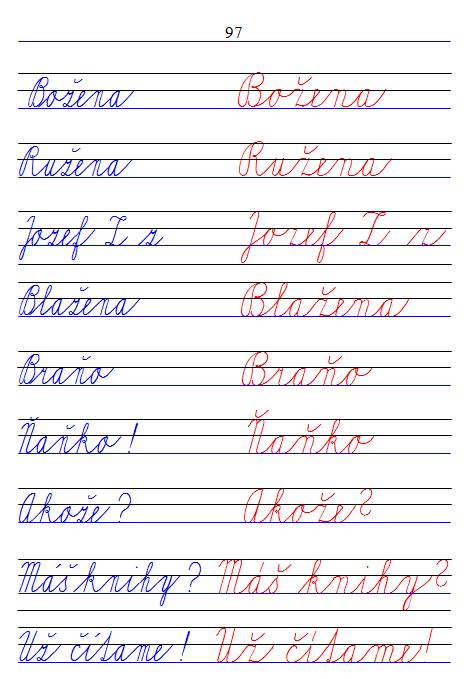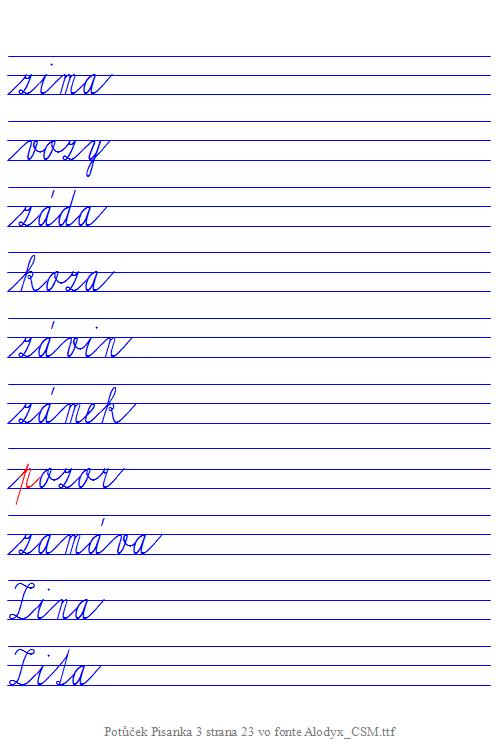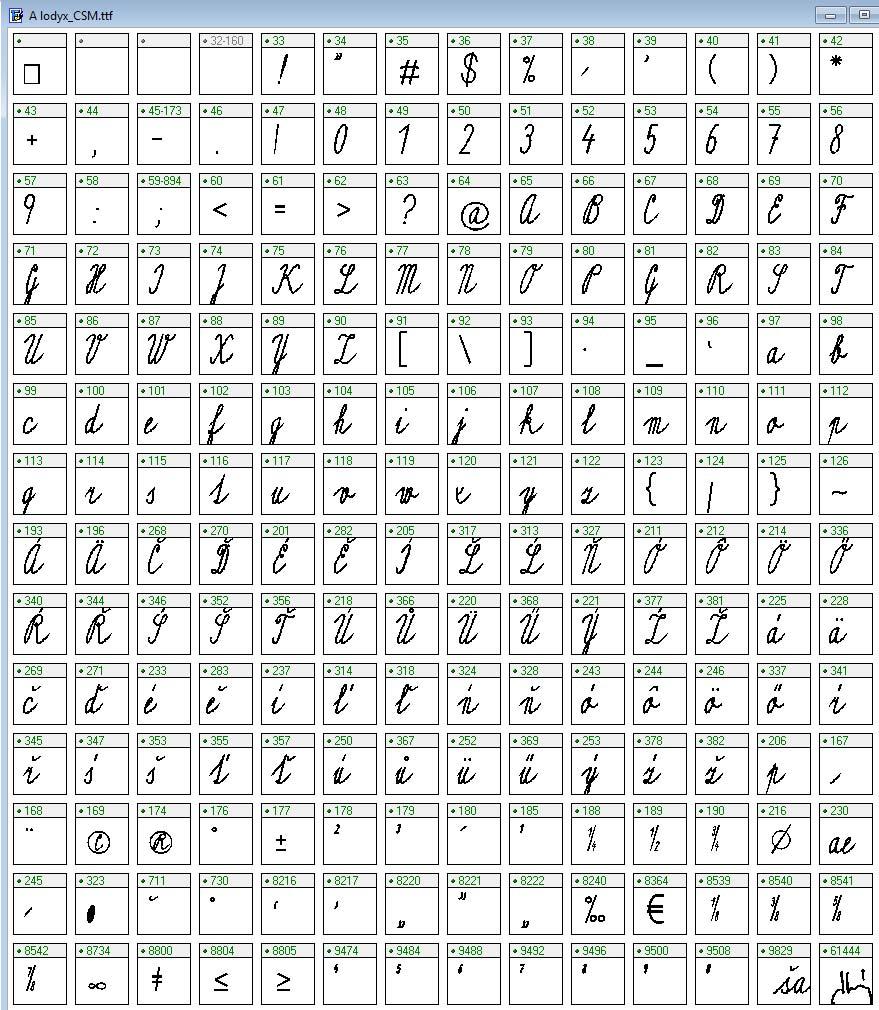
1 Font Alodyx úprava na verziu so slovenskými a maďarskými písmenami Stanislav Fila. Centrum pedagogicko-psychologického poradenstva a prevencie, Banská Bystrica. Font možno stiahnuť z lokácie: V súbore cti_me.txt je toto: Psací písmo TRUE TYPE alodyx. Zatím to nejlepší běžně dostupné ČESKÉ psací písmo. Jelikož některá psací písmena se v češtině napojují od spodu a některá ne, je zde použita klávesa ( VEDLE ENTERU! ) pro změnu tohoto napojení. Instalace pro méně znalé např: start/ovládací panely/písma/soubor/nainstalovat nové písmo lokace - vybrat Zařazeno do projektu - didaktické pomůcky. Používa teda len jednu nábehovú čiarku rovnakú pred písmenami ako aj za písmenami, ktoré to potrebujú. Túto čiarku dal autor pod klávesu. Tzv. doťahovaciu čiarku na konci písmen nepoužíva. Písanie v ňom je teda jednoduchšie ako vo fonte Abeceda.ttf. Autor fontu nie je známy. Iba krstné meno Ladislav a nickname (prezývka) šaman. Podpis a nickname má pod kódmi: Nicname: Priezvisko: Krstné meno: Pretože font neobsahuje písmená slovenskej a maďarskej abecedy, tak som ich tam doplnil. Font som nazval A lodyx_csm (české-slovenské-maďarské písmená). Vo fonty boli niektoré Postripts Name česky. Najprv som ich premenoval na anglické, kvôli prehľadnosti pri pridávaní nových znakov. Pomôcka: acute = dĺžeň ú caron = mäkčeň č ring = kolečko ů circumflex = vokáň ô dieresis = dve bodky ü hungarumlaut = dve čiarky ű slash = lomítko / tilde = vlnovka ~ 1
2 Pritom som odstránil niektoré chyby. 1. Písmeno kód 318 lcaron ľ (l s mäkčeňom) bolo tam f : Opravil som to takto: 2. Znak ś (saucute) bol namapovaný ako scircumflex ŝ (kód 349). Dal som ho pod sacute (kód 347). 3. Znak dvojbodka nebol namapovaný. Namapoval som ho pod Postscript Name colon, kód 58. 2
3 Dorobil som tieto znaky: Ä Ľ Ĺ Ó Ô Ö Ő Ŕ Ü Ű Ź 11 znakov ä ĺ ľ ô ő ŕ ü ű ź 9 znakov quoteright (Alt ) 1 znak doťahovacia čiarka na konci písmen: pod Ampersand & kód Alt znak Prerobil som české p na slovenské a pôvodné české p som dal pod kód Alt spolu 1 znak 23 znakov. Vo fonte je znak nacute teda malé n s dĺžňom, ktoré sa v českej abecede nevyskytuje. ń kód 324. Nechal som ho tam. Pridal som tam aj pomocný ladiaci znak, ktorý som dal pod Nacute Ń kód 323. Problém sklonu dĺžňov. Keď sa na pôvodný font pozrieme, resp. napíšeme v ňom nejaký text, vidíme, že smer dĺžňov je príliš doprava, teda nelícuje so sklonom písma. Opravil som tento sklon u všetkých písmen s dĺžňom. Rozdiel vidno tu: Pôvodné dĺžne: 3
4 Upravené dĺžne: Vo fonte sú aj znaky, ktoré sa bežne vo lokalizovaných fontoch bežne nevyskytujú konkrétne: registered (0174) copyright (0169) notequal (8800) oslash neviem kód Ø kód 0216 nazval ho průměr dá sa cez Vložiť Symbol infinity (8734) plusminus (0177) ± lessequal (8804) greaterequal (8805) æ æ kód 0230 dá sa cez Vložiť Symbol perthousand (8240) uni00b9 ¹ kód 0185 nazval ho mocnina 1 dá sa cez Vložiť Symbol uni00b2 ² kód 0178 nazval ho mocnina 2 dá sa cez Vložiť Symbol uni00b3 ³ kód 0179 nazval ho mocnina 3 dá sa cez Vložiť Symbol onehalf ½ kód 0189 nechal anglický názov dá sa cez Vložiť Symbol onequarter ¼ kód 0188 nechal anglický názov dá sa cez Vložiť Symbol threequaters ¾ kód 0190 nechal anglický názov dá sa cez Vložiť Symbol oneeighth (8539) ⅛ threeeights (8540) ⅜ fiveeights (8541) ⅝ seveneights (8542) ⅞ heart (9829) nechal anglický názvov je tam dal nickname šaman unif004 (61444) tam dal svoje priezvisko unif005 (61445) tam dal svoje krstné meno Ladislav Tieto znaky dal autor pod tzv. pseudografiku SF (9474) nazval ho mocnina 4 zobrazí sa to vo fonte ako 4 SF (9484) nazval ho mocnina 5 zobrazí sa to vo fonte ako 5 SF (9488) nazval ho mocnina 6 zobrazí sa to vo fonte ako 6 SF (9492) nazval ho mocnina 7 zobrazí sa to vo fonte ako 7 SF (9496) nazval ho mocnina 8 zobrazí sa to vo fonte ako 8 SF (9500) nazval ho mocnina 9 zobrazí sa to vo fonte ako 9 SF (9508) nazval ho mocnina 0 zobrazí sa to vo fonte ako 0 Znaky som tam nechal. 4
5 Problém odsadenia veľkých písmen. Všetky veľké písmená sú v pôvodnom fonte odsadené: Posunul som medzeru pre nimi na minimum. Výsledok je tento: 5
6 Problém doťahovacej čiarky na konci písmen. Keď napíšeme napríklad tento text z knihy Maľovaná abeceda vyzerá takto: Vidíme, že písmenkám na konci slov kúsok chýba. Dorobil som preto pomocnú čiarku a dal som ju pod znak & (ampersand kód 38). Text s touto doťahovacou čiarkou vyzerá potom takto: (Prameň: Ján Smrek: Maľovaná abeceda. Vydalo vydavateľstvo Mladé letá Bratislava Siedme vydanie. S gramoplatňou druhé.) 6
7 Toto sú všetky znaky vo fonte Times New Roman; veľkosť písmen 12 bodov: Znaky vo fonte Alodyx_CSM; veľkosť písma 20 bodov: Je to vložené ako obrázky, aby to bolo vidno aj pri nenainštalovanom fonte. 7
8 Prevod tlačeného textu do písaného fontu Alodyx_CSM pomocou makier. Aj keď písanie v tomto fonte priamo je oveľa jednoduchšie ako napríklad vo fonte Abeceda.ttf, predsa len pri dlhších textoch je to prácne aj keď používame len jednu spojku a tiež ak používame aj doťahovacie čiarky na konci písmen. Postup. Preto som urobil na to vo Worde makrá, ktoré tlačený text do tohto fontu prevedú. 1. Natiahneme do Wordu súbor, kde sú makrá, napríklad: Alodyx_CSM_Vzor_A4_makra_prazdny.doc 2. Súbor uložíme pod iným názvom aby sme si vzor nezničili napríklad: Alodyx_CSM_Adam_v_skole_nesedel.doc. 3. Napíšeme text v nejakom fonte napríklad Times New Roman, teda inom než Alodyx. (Inak mohli by sme ho napísať aj priamo vo fonte Alodyx_CSM, ale bez tých lomiek na začiatku a doťahovacej čiarky na konci. Makro to nekontroluje. Ale je to menej prehľadné.) Maľovaná Abeceda. Adam v škole nesedel, Abecedu nevedel, prišli k nemu líšky, čítali mu z knižky. Ján Smrek 4. Uložíme ho napr. ako: Alodyx_CSM_Adam_v_skole_nesedel_tlacene.doc ak by sme sa potrebovali k nemu vrátiť. Napríklad zistíme, že tam máme chybu. 5. Stlačíme Alt + Q čím spustíme tzv. Riadiace makro. Objaví sa oznam: Ak chceme skončiť, stlačíme Nie. 8
9 Ak chceme pokračovať, stlačíme Áno. Objaví sa oznam: Ak chceme skončiť, stlačíme Zrušiť. Ak nechceme vidieť štatistiku znakov a pokračovať v prevode, stlačíme Nie. Ak chceme vidieť štatistiku znakov stlačíme Áno. Objaví sa Tabuľka znakov v texte: Stlačíme OK. Objaví sa oznam o voľbe veľkosti fontu: Preddefinovaná (default) hodnota je 28 bodov. Ak chceme inú veľkosť zadáme ju a stlačíme OK. Alebo priamo stlačíme OK. 9
10 Makrá prevedú text a po a po určitom čase sa objaví oznam: Ak nechceme doplniť doťahovacie čiarky, stlačíme Nie. Ak ich chceme doplniť stlačíme Áno Program dopĺňa čiarky a potom sa objaví oznam: Ak ich nechceme zarovnať, stlačíme nie. Inak stlačíme Áno. Program zarovná písmenká, vidíme ako sa tam objavuje a mizne ten pomocný znak. Keď ich zarovná objaví sa oznam: 10
11 Poznámka. Makrá označujú písmenká, ktorých sa nejako dotklo tak, že ich vyfarbia na červeno. Keď dáme Nie, písmo sa vytuční a vyčierni. Keď stlačíme Zrušit, písmenká sa len vyčiernia. V každom prípade sa potom ešte sa objaví informácia: Stlačíme OK a prevod skončí. Súbor uložíme napr. pod názvom: Alodyx_CSM_Adam_v_skole_nesedel_pisane_1.doc. Vidíme toto: 11
12 Keď písmo vymodríme, to už urobíme normálne vo Worde, tak dostaneme toto: Súbor uložíme napr. pod názvom: Alodyx_CSM_Adam_v_skole_nesedel_pisane_2.doc. Písmo môžeme aj vytučniť. 12
13 Teraz sa nám zdá tá veľkosť 28 bodov príliš veľká a chceli by sme to zmeniť na 20 bodov. Označíme celý text (Ctrl+A) a dáme veľkosť písma 20. Veľkosť písma sa zmenší, ale nesedí zarovnanie písmen na začiatku riadkov. (Viď súbor: Alodyx_CSM_Adam_v_skole_nesedel_pisane_3.doc). Na to je určené makro opakovaného prevodu, ktoré vyvoláme stlačením kombinácie Ctrl + Alt + W. Makro začne zarovnávať a vidíme pomocné znaky. Po skončení dá oznam: 13